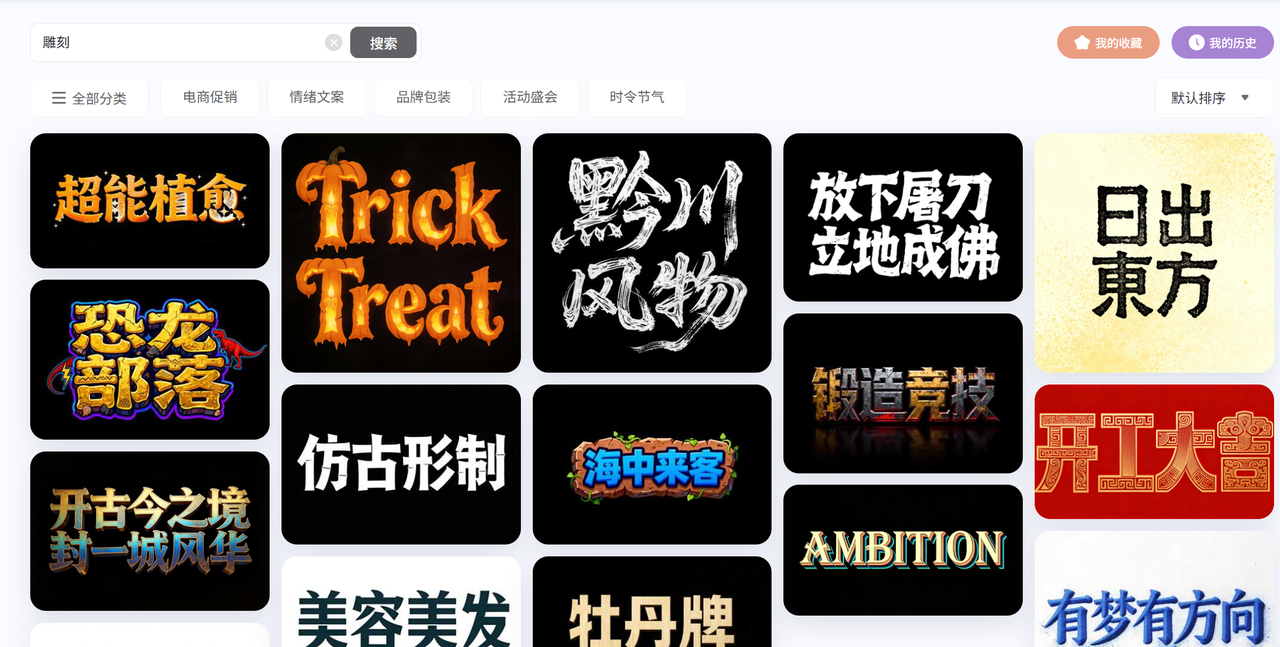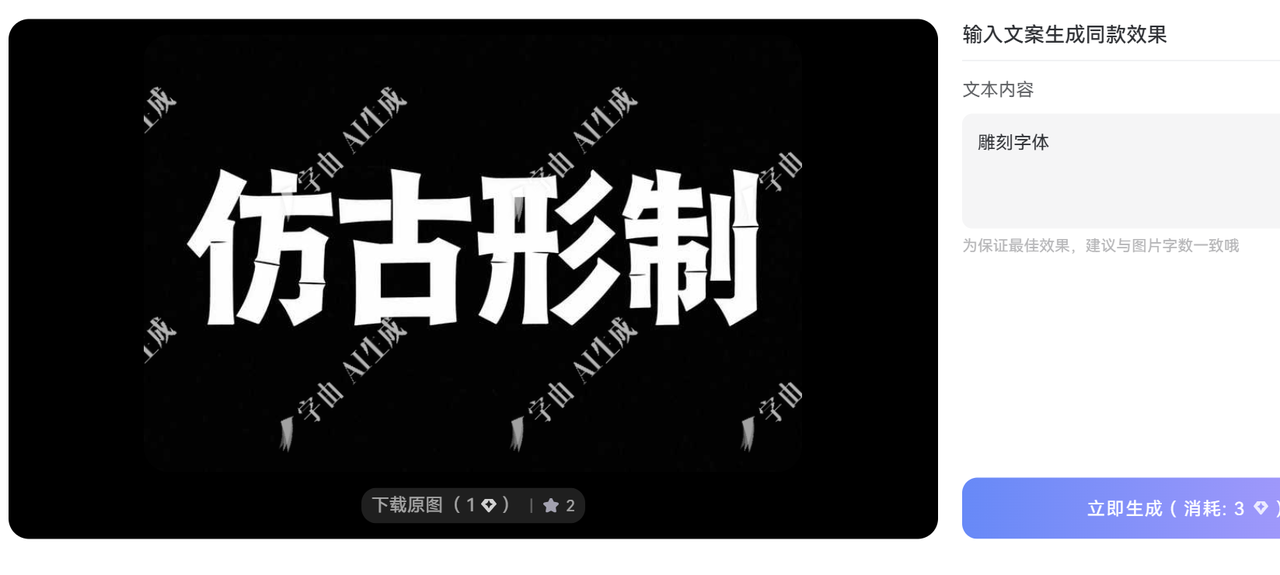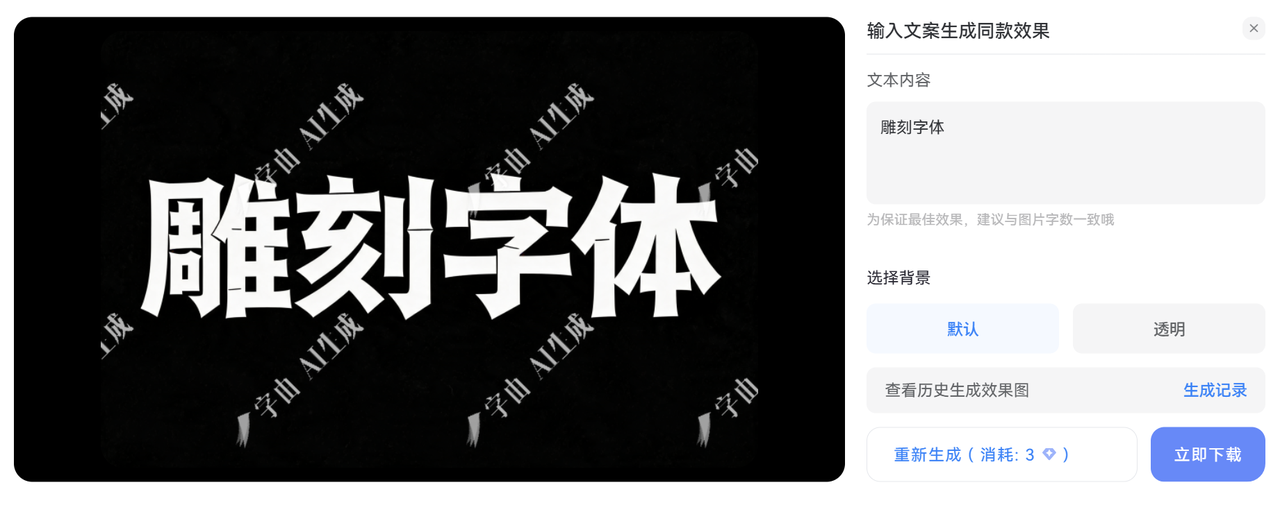
如何下载免费商用的雕刻字体?字由AI生成与4个网站推荐
无论是制作标识、海报,还是装饰文字,雕刻字体都能赋予作品独特的质感和艺术感。许多朋友在寻找“免费商用的雕刻字体下载”时,常常遇到版权限制、字体样式单一或者使用不便的问题。本文给大家介绍一个AI生成雕刻字体的方法,以及几个可以下载雕刻字体的网站。
字由的AI字体设计功能,通过提供大量的雕刻字体模板样式,替换文字,就能一键生成同款雕刻字体。
- 多样化选择
平台里涵盖了多种雕刻字体样式,满足不同风格需求。
我自己用过几次,发现生成的字体清晰且有层次感,尤其适合制作带有复古或工业风的设计。导出格式多样,可以直接应用到海报、包装设计、网页或视频字幕中,节省了大量调整时间。